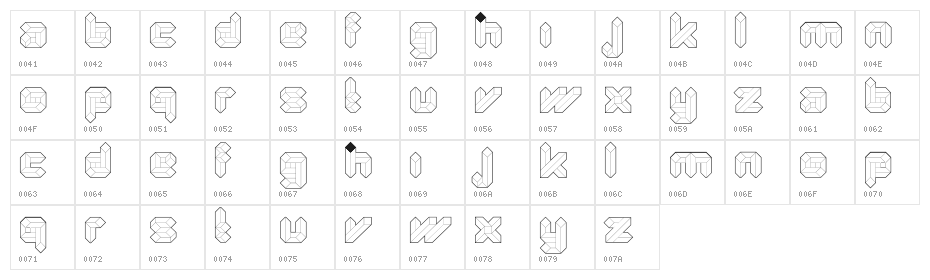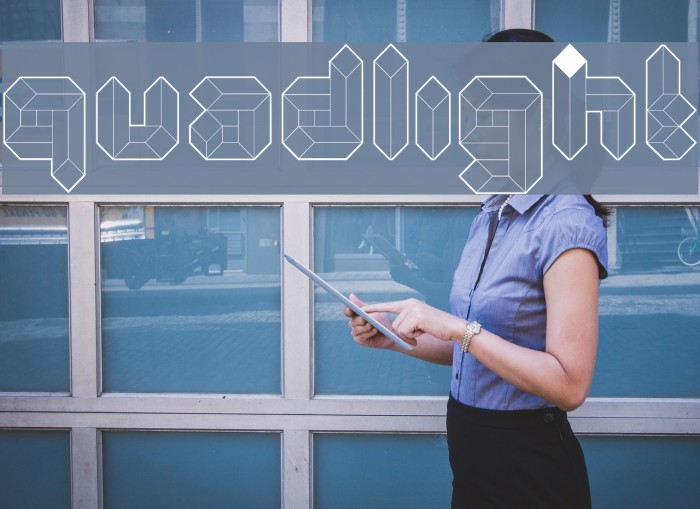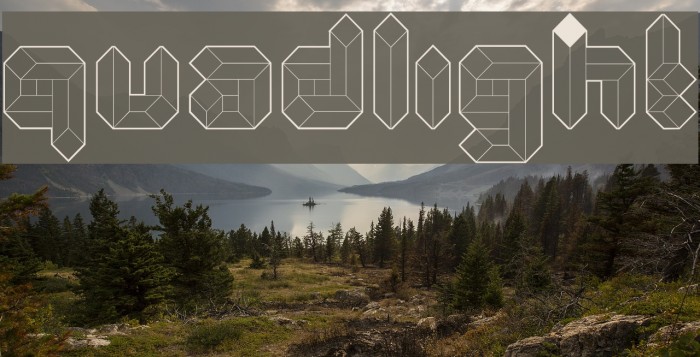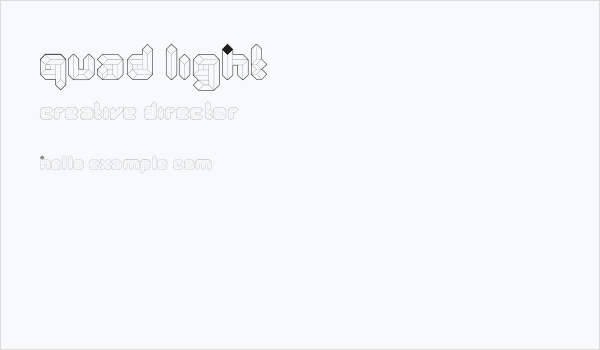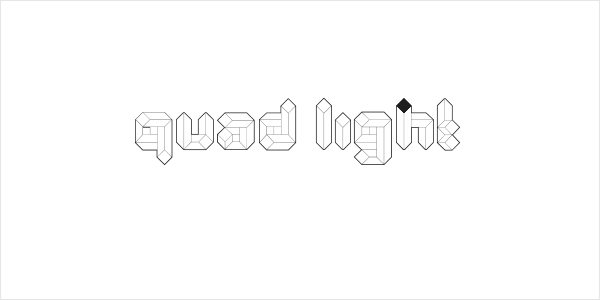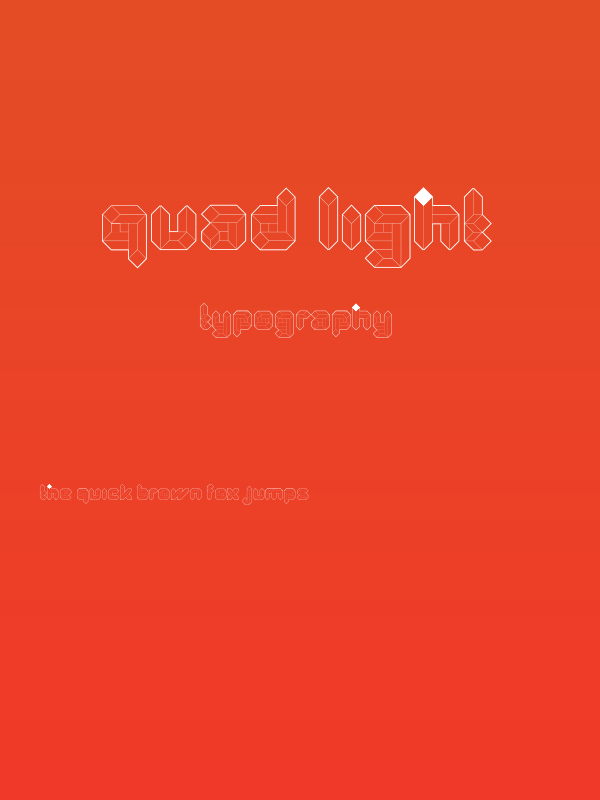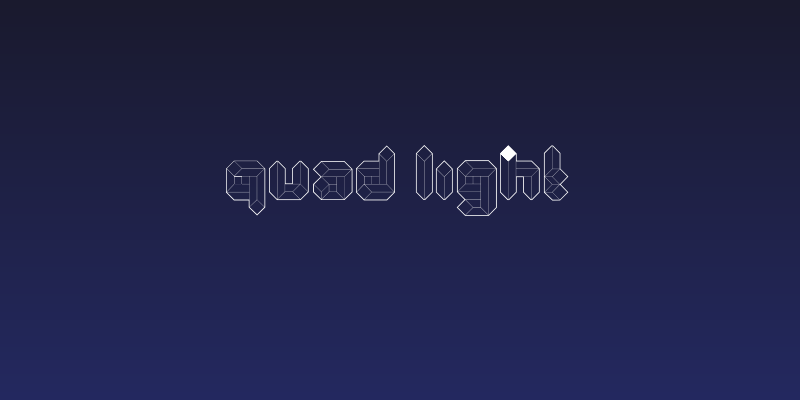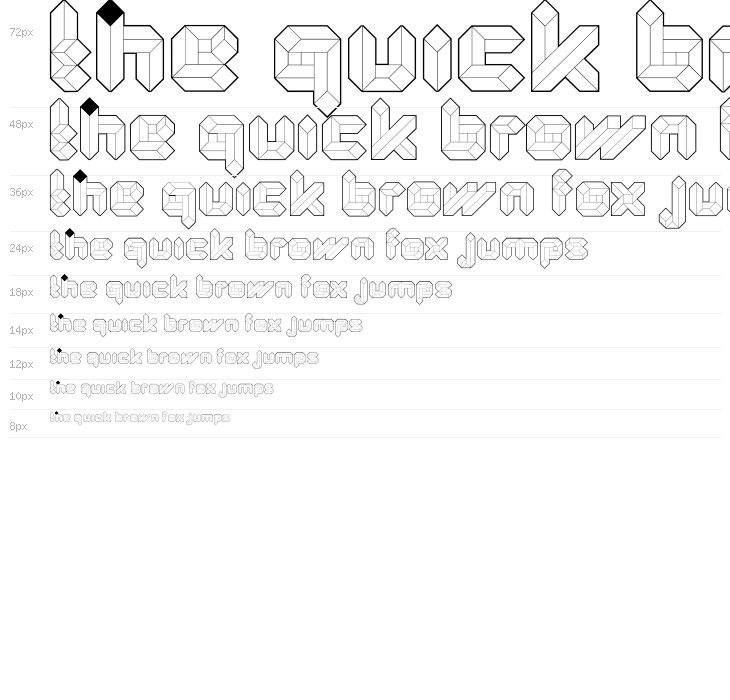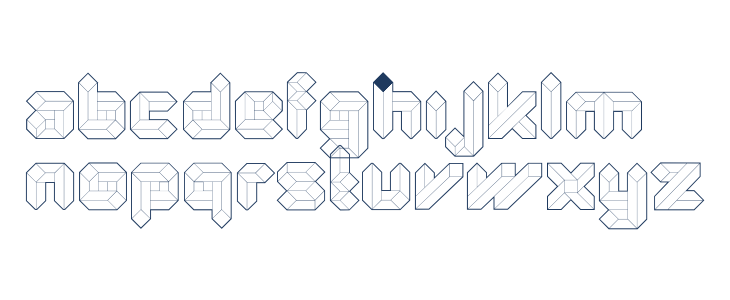
Quad-Light Font
| Область применения | Logos, Headlines, Posters |
| Рекомендуемые проекты | Ideal for futuristic branding, architectural designs, tech-related projects, and modern art installations. |